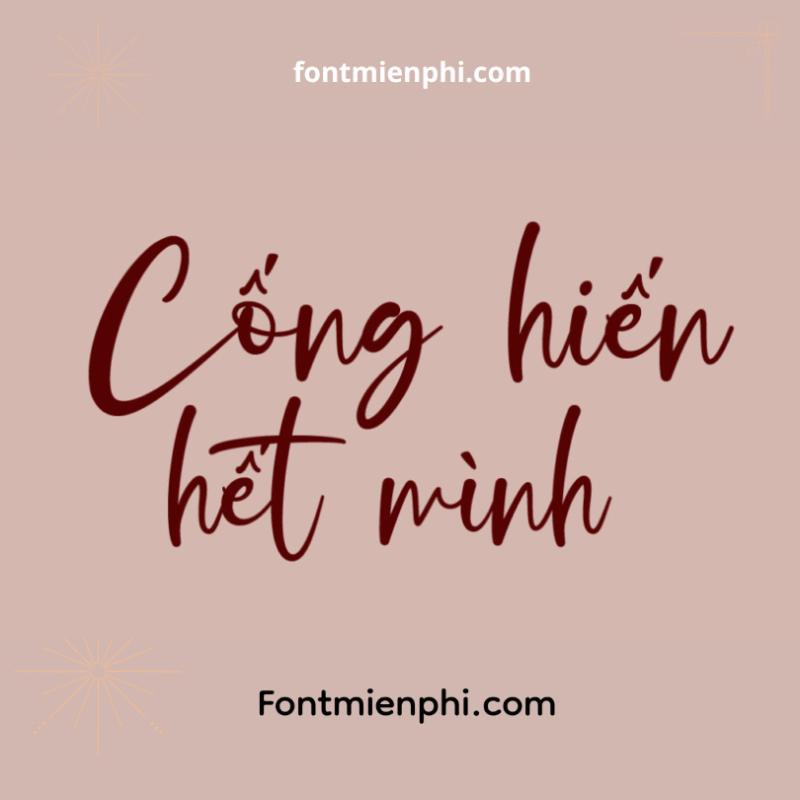
Font Việt hóa 1FTV VIP Gillastone
Font 1FTV VIP Gillastone là bộ font Việt hóa cao cấp, thiết kế độc đáo với phong cách chữ sang trọng, sắc nét, phù hợp cho thiết kế đồ họa, logo, banner hoặc dự án nghệ thuật. Font hỗ trợ đầy đủ tiếng Việt (TV), đa dạng kiểu chữ (bold, italic, regular) và tương thích với nhiều phần mềm thiết kế.